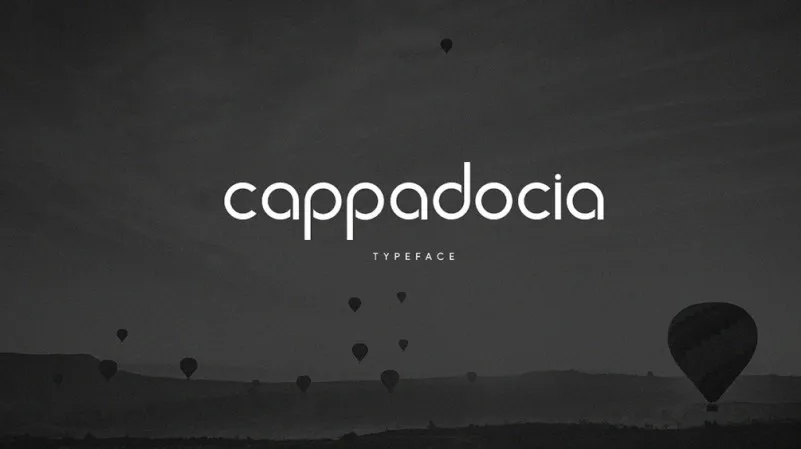
Cappadocia Sans Serif Font – Download Grátis
A Cappadocia Sans Serif é uma nova adição à família de fontes sans-serif que oferece tanto simplicidade quanto expressividade, sem perder sua beleza minimalista. Seu design com ângulos arredondados faz com que o formato atraia imediatamente para qualquer projeto gráfico que você esteja criando. Com apenas uma pequena alteração nos estilos de texto ou nas cores, é possível transformar seu design de um vintage para algo futurista e sci-fi em poucos minutos. Esta fonte minimalista oferece um visual incrível tanto para o corpo do texto quanto para logotipos, panfletos, headlines, capas de livros e revistas, cartazes e projetos de marca. Com a Cappadocia Sans Serif você pode criar designs contemporâneos que não apenas destacam seus textos, mas também transmitem uma forte mensagem visual. Sua simplicidade faz com que seja ideal para trabalhos que exigem um enfoque limpo e organizado, tornando-a uma escolha ótima tanto para novatos quanto para profissionais avançados no campo da design gráfico.